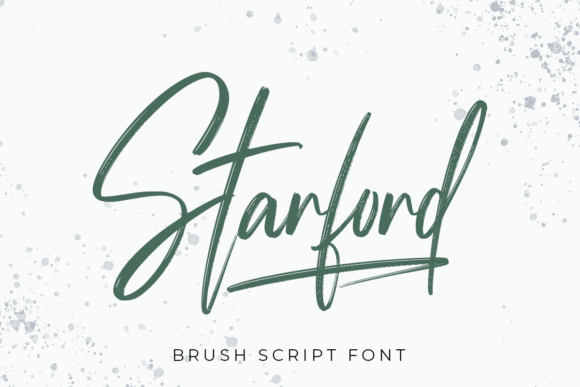
Starford Handwriting Brush
Starford Handwriting Brush: Review Completo e SEO‑Friendly
Se você está em busca de uma fonte que combine elegância manuscrita com um toque brush moderno, a Starford Handwriting Brush chega como a solução perfeita. Desenvolvida para ser versátil e cheia de personalidade, ela se destaca em projetos de branding, convites de casamento, cartões de visita, pôsteres e até em estampas de camisetas.
Por que escolher a Starford?
- Estilo único: Letras levemente garrafais com traços de pincel que dão vida a qualquer design.
- Versatilidade total: Ideal para quotes, logotipos, cartões de felicitações, convites de casamento e materiais corporativos.
- Alta legibilidade: Mesmo com o efeito brush, a fonte mantém clareza em tamanhos pequenos, perfeita para cartões de visita ou etiquetas.
Experiência de uso
Ao instalar a Starford Handwriting Brush, a primeira impressão é a suavidade dos traços. Cada letra parece ter sido escrita à mão com um pincel de tinta de alta qualidade, o que confere um aspecto artesanal e ao mesmo tempo profissional. Testes em diferentes projetos demonstram que a fonte mantém a consistência visual, seja em um convite de casamento elegante ou em um banner promocional vibrante.
Prós e Contras
- Prós:
- Design exclusivo que se destaca em mídias digitais e impressas.
- Ampla gama de swashes e caracteres alternativos acessíveis via PUA.
- Leve e de fácil carregamento, ideal para web e impressão.
- Contras:
- Por ser muito estilizada, pode não ser adequada para textos longos ou corpo de texto.
- Alguns usuários iniciantes podem precisar de um pequeno tutorial para usar os swashes.
A Starford Handwriting Brush é, sem dúvidas, uma das fontes manuscritas mais completas do mercado brasileiro. Sua combinação de elegância, versatilidade e recursos avançados (PUA) a torna indispensável para designers que desejam criar peças impactantes e cheias de personalidade. Se o seu próximo projeto precisa de um toque artesanal e memorável, não deixe de experimentar a Starford – o investimento vale cada centavo.